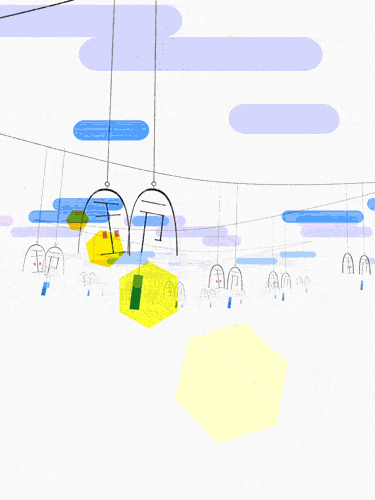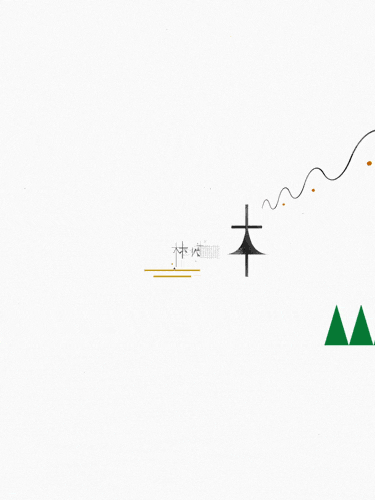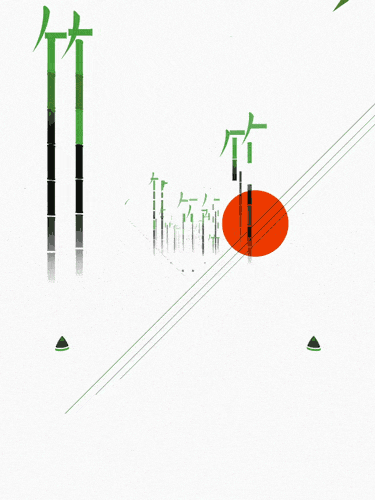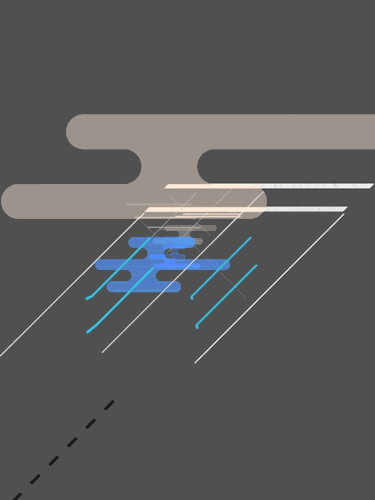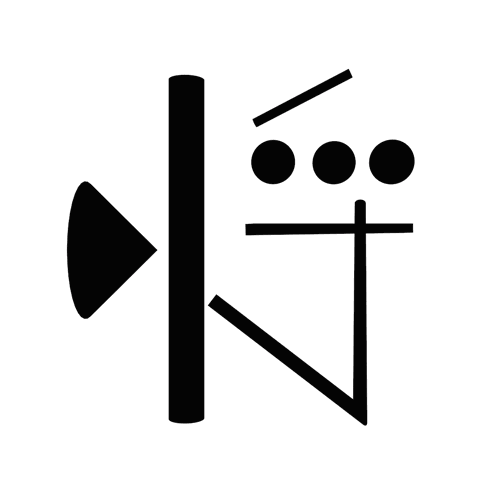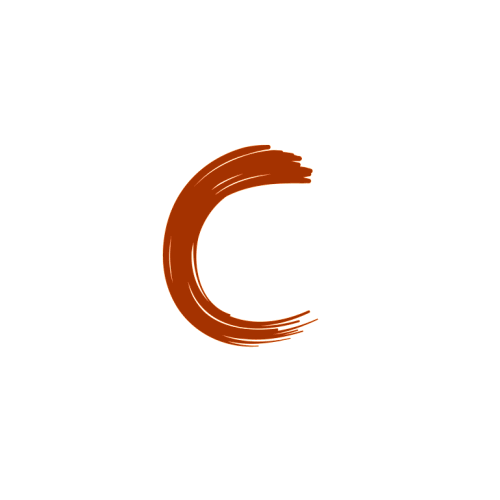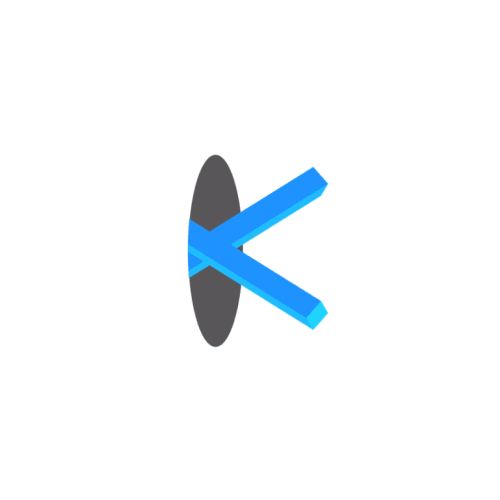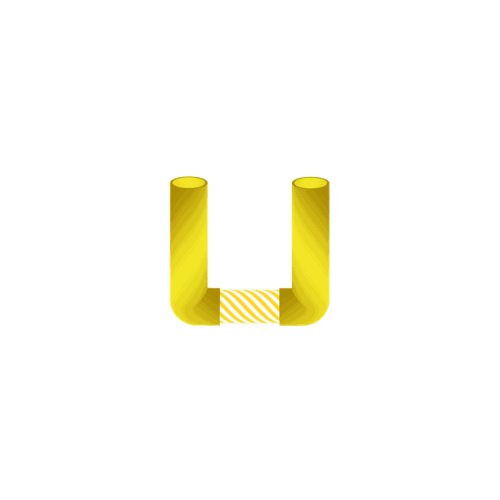
汉字是中国人的发明,80后日本设计师却用15 个跳舞的汉字
京都作为日本最受欢迎的城市之一,只有旅游旺季和旺旺季。没去过的童鞋们,从岛国设计师笔下的 这15 个跳舞的汉字,就能一览京都的城市特色了。
1、京
以「京」字开头,代表京都。京都是日本的古都,是日本历史最悠久的城市之一。
2、木
日本汉字中的「木」,跟汉语中意思相近,是树的意思。京都是日本绿色资源比较丰富的城市,这个动图就形象的表示出京都的林荫道路。
3、桜、梅、柳
「桜」是一个日本汉字,也写作樱,代表樱花;日本汉字里的「梅」不是汉语中的梅花,而是指李树;「柳」字跟汉语中是相同的,就是柳树。这三个字形象的表示出京都当地比较有代表性的植物。
4、川
桜、梅、柳结束之后,先是听到了水流声,然后看到这一条河的动画,这个动画是用「川」字画出来的,还有各种绿植、桥和小鸟,给人生机勃勃的感觉。
5、布
日式门帘有自己的特色,用「布」字做出小门帘的样式也是别出心裁的想法,布字既代表了门帘的原材料,也能形象的表现出门帘的样子。
6、铃
乍一看以为是金、今两个字,其实这是一个「铃」字,指代的是风铃。
7、伞
京都的油纸伞被各路游客都列入必买的纪念品清单,但是它不是从中国传过去的吗?
8、门
这两个都是「门」的造型,上面那个有点像有轨电车,下面这个则更像一个人在路面上慢慢行走,穿过一道道大门,仿佛下一次就能看到不一样的景致。
9、石
用一系列高低错落的「石」字表示民居,像是一个安静祥和的小村庄。
10、竹
京都当地有很多可供观赏的「竹」林,还有可以放慢脚步散步的竹林小道,想想就很惬意。
11、雨
从「雨」开始,设计师带大家进入了京都的夜晚,在背景色上也采用了纯黑色。
12、寺
日本汉字中的「寺」是塔的意思,动图中的原型就是京都的五重塔,这是从中国唐朝学习的成果。五重塔是京都代表性建筑之一,号称「日本三大名塔」之一。
13、塔
日本汉字中的「塔」跟中文指代的也不是一个东西,从动图中看,这里的塔代表灯笼。京都是一个庙会众多的城市,灯笼则是庙会中不可缺少的。
14、京女
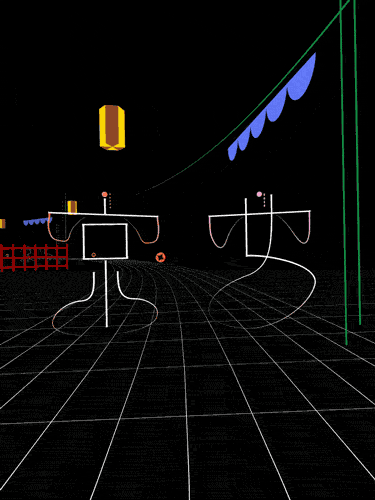
夜深了,该回家了。这个「京女」跟字面意思一样,就是京都女子,这个动画让人忍不住脑补日剧女主角乘电车回家的场景。
15、火
用简简单单的「火」字就营造出了烟花绚烂的景色。
这一系列汉字的动图设计师叫井口浩太,是一个笑起来很可爱的 80 后设计师,平面设计、空间设计、网页设计、影像设计都很拿手,简直是全才,最大的爱好就是写写字,所以才萌生出将汉字与动画相结合的灵感,让呆板的汉字瞬间就有了生命力。
这个汉字动画的作品一经问世就受到了大家的关注,这个设计师也越来越有兴致,不仅有汉字的动画作品,还有了英文的。
将来两个字像是一个立方体的两面:
一个大大的 C:
字母 K 也这么调皮,要出来又不出来的:
用来回穿梭的人串联起字母 U :
这个是 M 还是 W ?有多少人傻傻分不清楚。
N 像是一个机器人,垮掉但是依旧顽强的站起来:
这个字母 O 的灵感一看就知道来自于水边的夕阳:
这个日本设计师把日本汉字设计的这么漂亮,作为中国人却提笔忘字,写字龙飞凤舞,这样想来是不是有点惭愧呢?